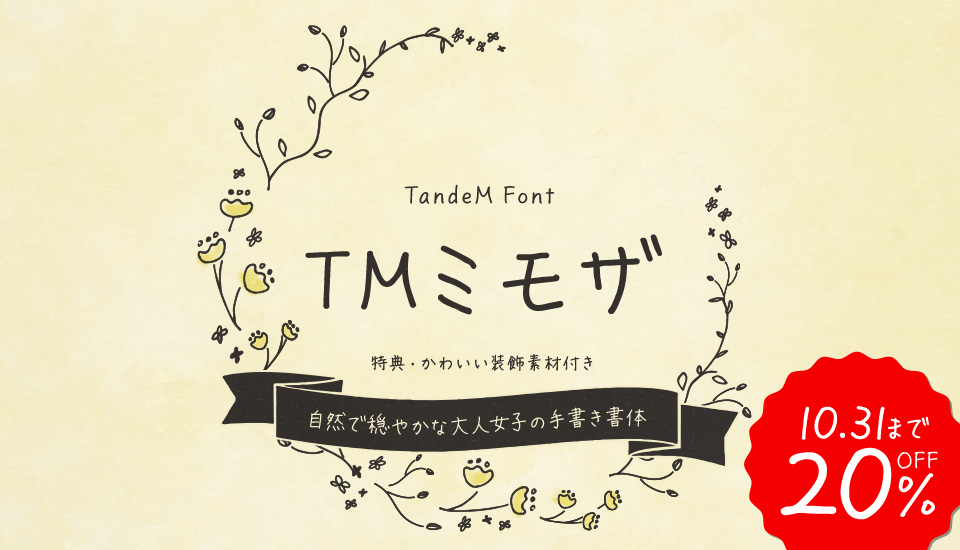
タンデムフォント TMミモザ
細めのペンで書いた、自然で穏やかな大人女子の手書き書体
細めのペンのにじみを残した、自然で穏やかな手書き文字です。まるで大人の女性の直筆ような手書き感たっぷりのTMミモザは、POP、宛名書き、挨拶分、動画配信のテロップ、SNS用の写真にも最適です。柔軟な使用許諾で、印刷物、WebサイトはもちろんYouTubeなどの動画も追加料金なしで利用可能です。
TMミモザの特徴
TMミモザL
TMミモザR
TMミモザB
癖は強すぎず、丁寧で穏やかに
手書き文字はその人のキャラクターを想起させます。お習字っぽくない、気負わない、丁寧な書きぶりが読み手に穏やかに届きます。
3種の太さで使い勝手良好!
インクのにじみを残したナチュラルな風合いです。文字の大きさによってペンを使い分ける想定です。
基本字形の Lightを太らせ、重なり合う線を一文字一文字調整しましたがこのアンカーポイントを整理整頓する作業にかなり時間を費やしました。
太らせるごとにアンカーポイントを整理して自然なインクのにじみを目指しました。
仮名は小さく、漢字は大きく。手書きのバランスを再現。
手書きの文章は、仮名を小さく書かれることが一般的なので画数の多い文字は無理なく自然に大きく設計しました。
アルファベットや数字も大きめで和欧混植もキレイです。
Adobe-Japan1-3準拠の充実した収録文字
よく使われる旧字体や人名漢字も多数収録するAdobe-Japan1-3準拠の文字セット。JIS2004字形のStdNフォントです。(例:一般的なアプリケーションソフトで使うと、「辻」は2点しんにょうで表示されます)